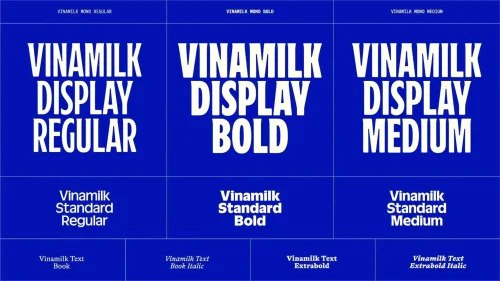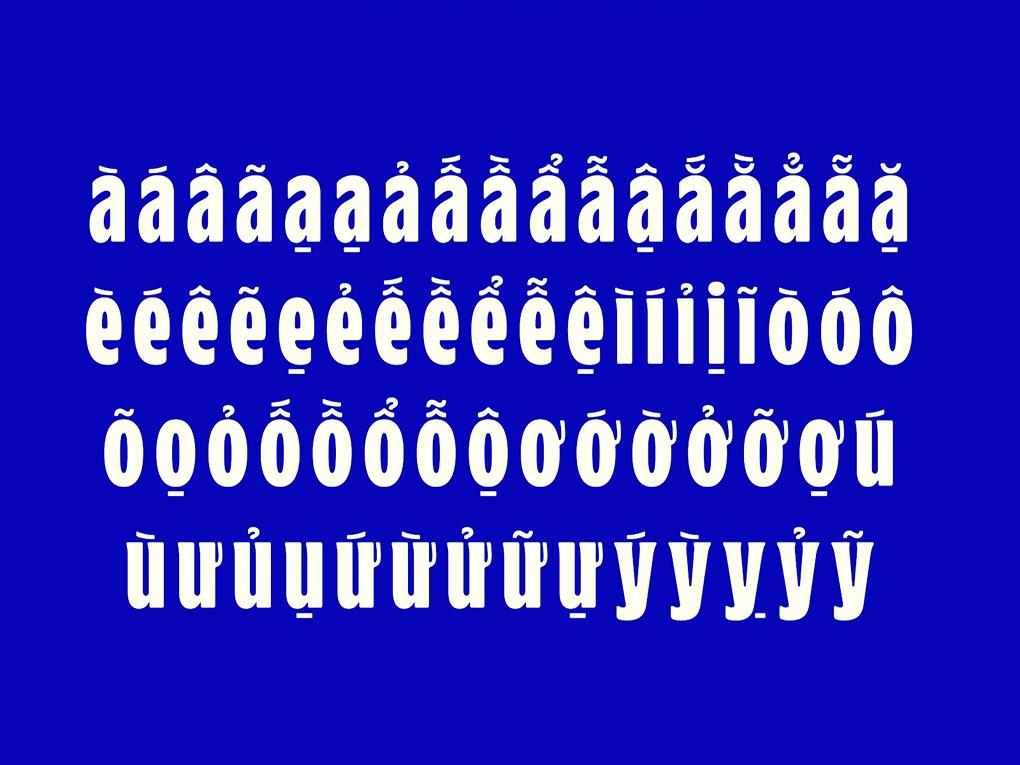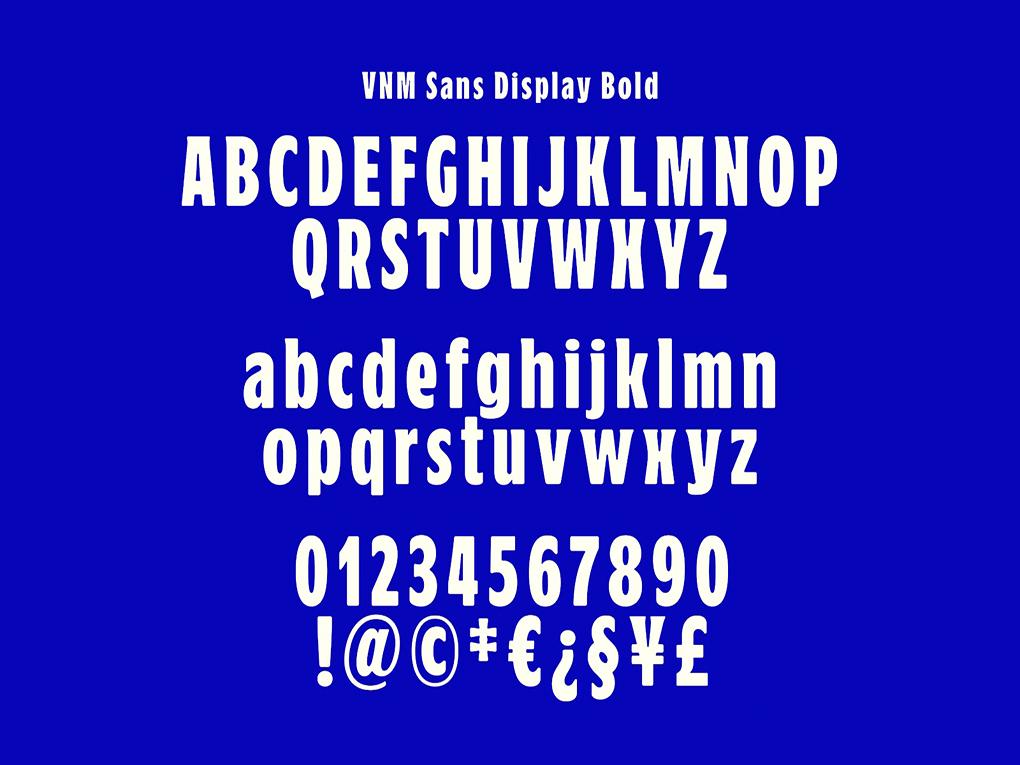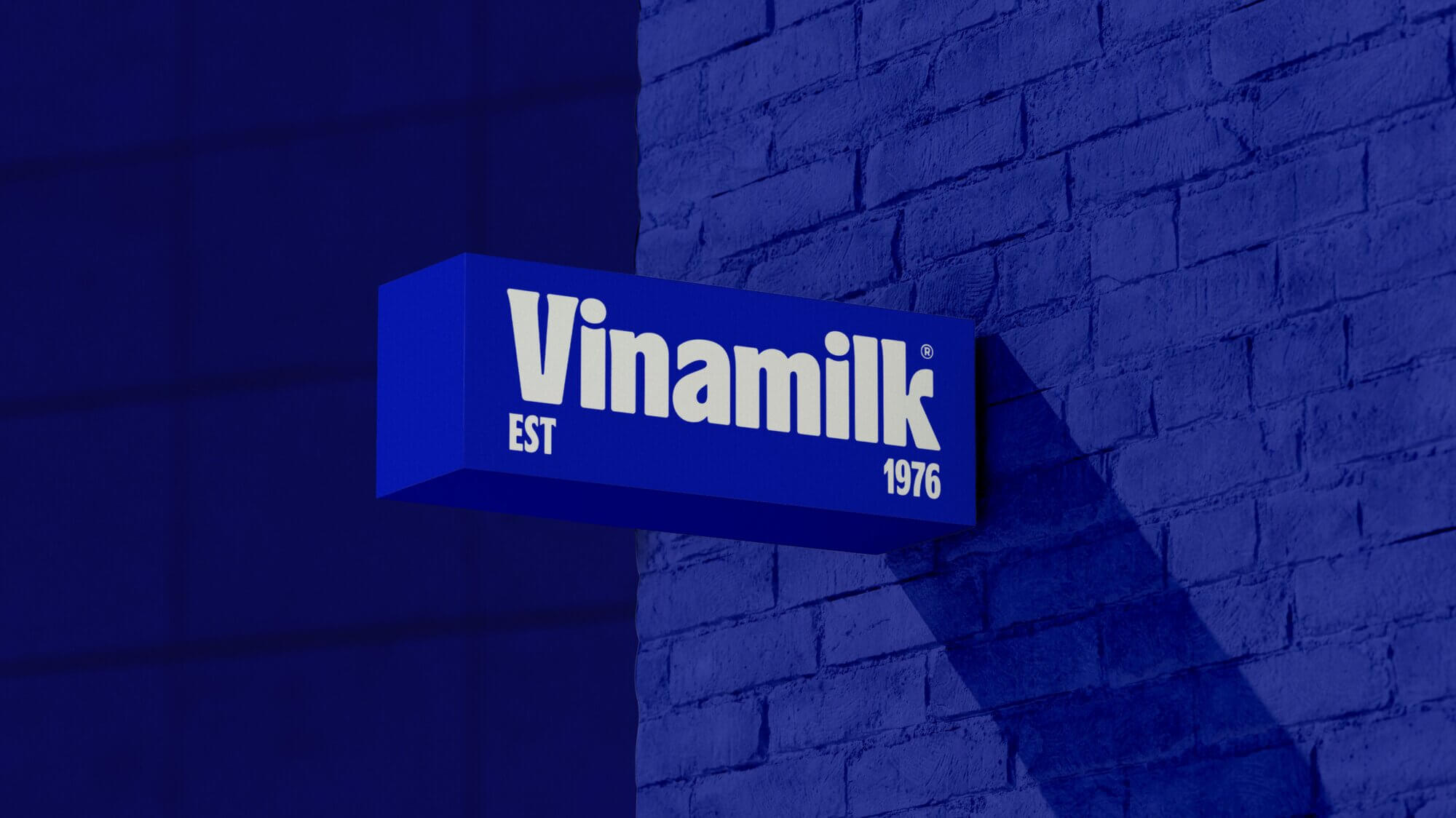
VNM Sans Std Font là bộ phông chữ không chân (Sans-serif) độc quyền nằm trong chiến dịch tái định vị thương hiệu mang tính lịch sử của Vinamilk, được thiết kế bởi Studio Koto kết hợp cùng các chuyên gia Typography hàng đầu Việt Nam. Với cấu trúc hình học hiện đại, các nét cong mô phỏng nụ cười thân thiện và tính nhận diện thị giác cực mạnh, phông chữ này nhanh chóng tạo nên cơn sốt trong giới thiết kế bao bì và truyền thông tiếp thị. Doozypack.vn cung cấp link download font Việt hóa VNM Sans Std chuẩn kỹ thuật, giúp bạn sở hữu phông chữ thời thượng này để thỏa sức sáng tạo các dự án bao bì mà không gặp bất kỳ lỗi hiển thị dấu tiếng Việt nào.
Đặc điểm thẩm mỹ độc đáo của bộ font VNM Sans Std
VNM Sans Std không chỉ là một phông chữ doanh nghiệp thông thường; nó là biểu tượng cho sự chuyển mình trẻ trung, năng động và đầy tự hào của thương hiệu quốc gia Việt Nam.
Phong cách Geometric Sans-serif trẻ trung và tràn đầy sức sống
Đặc trưng lớn nhất của VNM Sans Std Font là cấu trúc chữ dựa trên các khối hình học cơ bản nhưng được làm mềm bằng những đường nét uốn cong tự nhiên. Thân chữ thẳng đứng, tỷ lệ x-height lớn mang lại cảm giác vững chãi, rõ ràng và cực kỳ dễ đọc. Nét chữ đồng đều tạo nên một nhịp điệu Typography vô cùng minh bạch, hiện đại và tươi mới, rất phù hợp với các dòng sản phẩm tiêu dùng nhanh (FMCG), thực phẩm và đồ uống dinh dưỡng.
Những nét biến tấu “nụ cười” thân thiện và giàu cảm xúc
Điểm nhấn đắt giá nhất của phông chữ này nằm ở phần kết thúc của các chữ cái như ‘a’, ‘e’, ‘g’, nơi các đường nét được uốn cong nhẹ nhàng như một nụ cười rạng rỡ. Chi tiết cách điệu tinh xảo này giúp xóa bỏ hoàn toàn sự khô cứng của các phông chữ kỹ thuật số, mang lại cảm giác ấm áp, gần gũi và lan tỏa năng lượng tích cực đến người tiêu dùng ngay từ cái nhìn đầu tiên trên bao bì.
Ưu điểm vượt trội của bản font VNM Sans Std Việt hóa
Được thiết kế từ gốc để tôn vinh ngôn ngữ mẹ đẻ, việc tải font VNM Sans Std Việt hóa mang lại lợi thế hoàn hảo cho các nhà thiết kế trong nước:
- Hệ thống dấu tiếng Việt bản địa hoàn mỹ: Khác với các font chữ ngoại quốc phải qua khâu Việt hóa lại, VNM Sans Std được thiết kế dấu câu ngay từ đầu. Từng dấu sắc, huyền, hỏi, ngã, nặng đều được tính toán chuẩn xác theo độ cao thân chữ, bảo đảm không bị đè nét hay làm gãy bố cục dòng chữ.
- Khả năng ứng dụng đa cấp độ: Phông chữ hoạt động xuất sắc ở cả kích thước tiêu đề cực lớn trên các bảng quảng cáo ngoài trời lẫn kích thước siêu nhỏ trên bảng thành phần dinh dưỡng của vỏ hộp sữa.
| Biến thể Font | Đặc điểm thị giác | Ứng dụng đề xuất tại Doozypack.vn |
| VNM Sans Std Regular | Cân đối, thông thoáng, dễ đọc | Dùng cho nội dung hướng dẫn sử dụng, bảng thành phần (Body text). |
| VNM Sans Std Bold | Dày dặn, vững chãi, nổi bật | Dùng làm tiêu đề chính, tên sản phẩm hoặc logo thương hiệu. |
| VNM Sans Std Light | Thanh mảnh, tinh tế, hiện đại | Dùng cho các thông số phụ, mã vạch, chứng chỉ chất lượng. |
03 Ứng dụng thực tế của font VNM Sans Std trong sản xuất bao bì
- Bao bì ngành Sữa & Nước giải khát: Tiêu đề thương hiệu in bằng VNM Sans Std Bold kết hợp màu sắc tươi sáng trên nền hộp giấy Ivory mang lại cảm giác năng động, sạch sẽ và an toàn sức khỏe.
- Hộp giấy bánh kẹo & Đồ ăn vặt: Nét chữ vui tươi kích thích sự hào hứng của người tiêu dùng trẻ tuổi và các em nhỏ, giúp sản phẩm nổi bật hoàn toàn trên kệ hàng.
- Túi giấy bán lẻ & Quà tặng doanh nghiệp: Tên cửa hàng in bằng font VNM Sans Std trên túi giấy trắng cán màng mờ tạo phong cách tối giản, hiện đại và chuyên nghiệp.
Lưu ý kỹ thuật khi in ấn với phông chữ hình học VNM Sans Std
Việc sản xuất bao bì thực tế sử dụng các phông chữ hiện đại đòi hỏi sự am hiểu kỹ thuật chuyên sâu tại xưởng in Doozypack.vn: